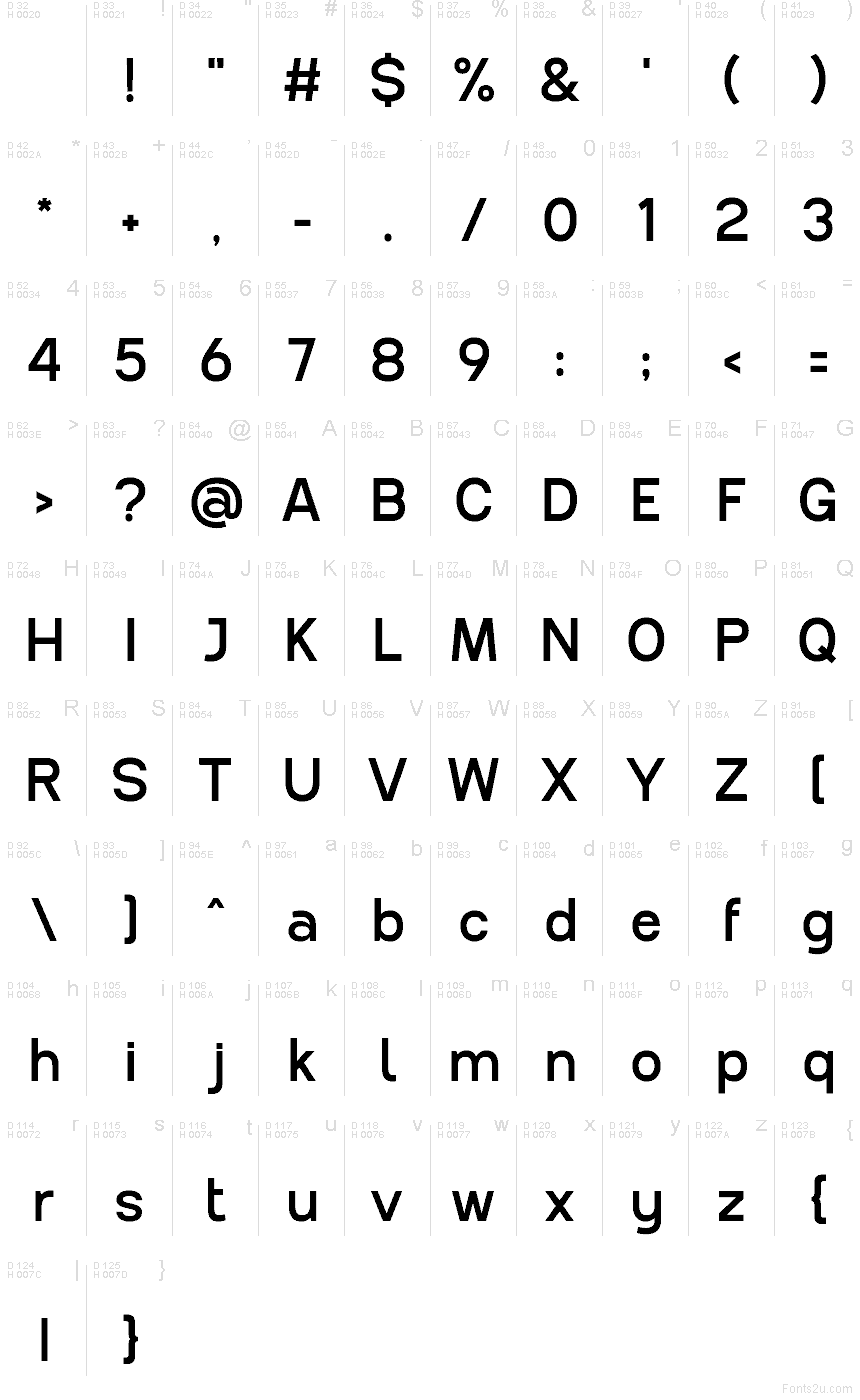
A Poltab Semi Bold, da Poltab (Glyphminds Studios), é uma fonte geométrica sem serifa gratuita com um toque amigável e despojado. Suas letras baseiam-se em traços amplos e uniformes e formas quase circulares, enquanto as verticais altas e retas garantem um visual limpo e contemporâneo, sem parecer excessivamente suave ou casual.
É perfeita para branding, embalagens, cabeçalhos de apps, títulos de cartazes e chamadas editoriais onde se busca um tom moderno sem frieza. Como é uma fonte gratuita, funciona muito bem em logotipos, capas e cartões de título, já que o "o" arredondado e o ritmo aberto e robusto dão às palavras curtas uma presença calma e marcante.